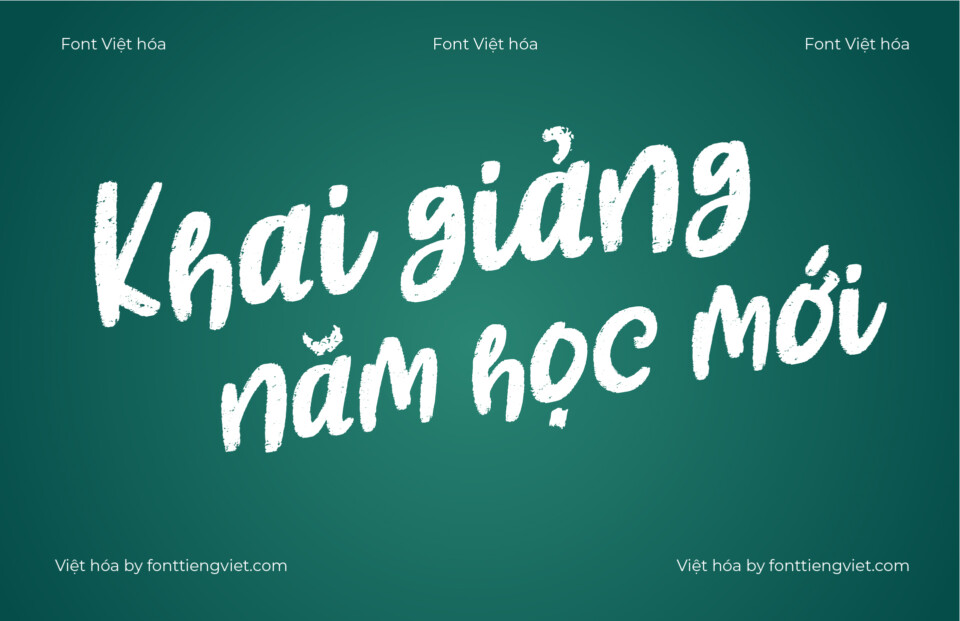
Font Việt hóa 1FTV VIP Yearbook – Phấn
Giới thiệu về Font Việt hóa 1FTV VIP Yearbook – Phấn
Trong những ngày cuối cấp, việc lưu giữ những kỷ niệm học đường luôn là ưu tiên hàng đầu của các bạn học sinh. Để tạo nên một cuốn kỷ yếu ấn tượng, việc lựa chọn Font Miễn Phí phù hợp đóng vai trò cực kỳ quan trọng. Font Việt hóa 1FTV VIP Yearbook – Phấn chính là lựa chọn hoàn hảo nhất để tái hiện lại không khí lớp học thân thương qua những nét vẽ tay mộc mạc và chân thực.
Đặc điểm nổi bật của bộ font chữ viết bảng
Font Việt hóa 1FTV VIP Yearbook – Phấn được thiết kế dựa trên mô phỏng nét phấn viết bảng truyền thống. Với các đường nét có độ nhám tự nhiên và không đều, bộ chữ mang lại cảm giác hoài niệm, ấm áp như những dòng lưu bút viết vội trên bảng đen. Font chữ này đã được tối ưu hóa tiếng Việt hoàn chỉnh, giúp các bạn dễ dàng gõ dấu mà không lo bị lỗi hiển thị hay mất nét trong quá trình thiết kế đồ họa.
Cách ứng dụng Font Việt hóa 1FTV VIP Yearbook – Phấn trong thiết kế
Với phong cách giáo dục đặc trưng, bộ font này cực kỳ phù hợp cho các dự án liên quan đến trường học. Bạn có thể sử dụng Font Việt hóa 1FTV VIP Yearbook – Phấn để làm tiêu đề cho các trang kỷ yếu, thiết kế thiệp mời họp lớp hoặc tạo các hình ảnh chia tay đầy cảm xúc trên mạng xã hội. Sự kết hợp giữa nét chữ phấn và phông nền tối sẽ tạo nên hiệu ứng thị giác mạnh mẽ, thu hút người xem ngay từ cái nhìn đầu tiên.